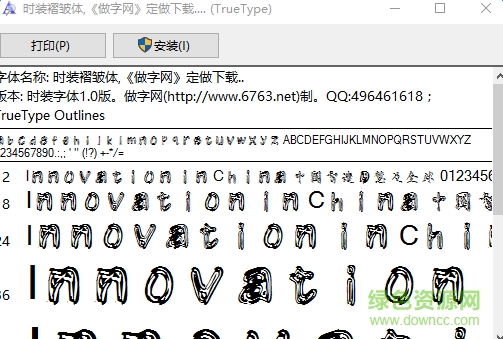
時裝褶皺體是時裝字庫中一款很有特色的電腦字體,這款字體寫出來的字就像它的名字所說那樣是褶皺在一起的,這也是它的一個重要特點(diǎn),喜歡這款字體的朋友可以來綠色資源網(wǎng)下載。
時裝褶皺體真的是一款很不錯的電腦字體,可以用于很多方面,不管是藝術(shù)設(shè)計還是廣告設(shè)計都是很合適的,歡迎大家來綠色資源網(wǎng)在做。